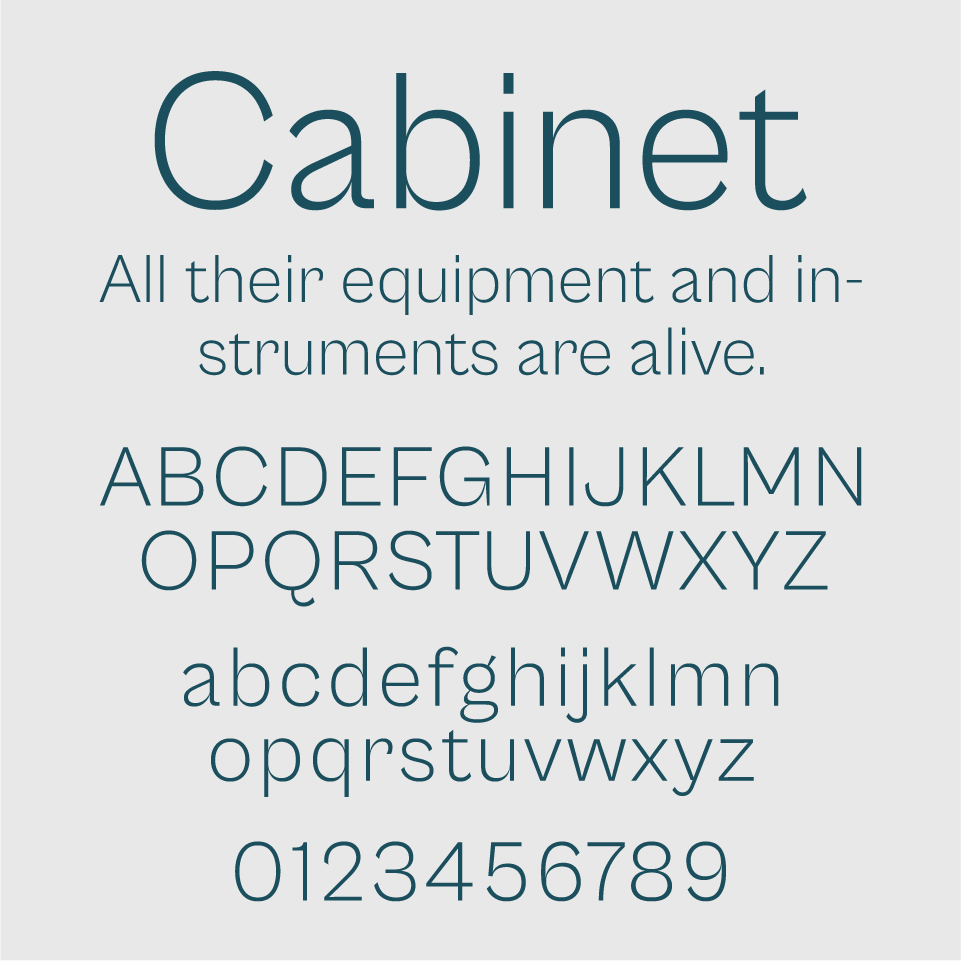
Cabinet Groteskフォントは、どこかクラシカルな雰囲気と現代的なシャープさが同居する、スマートなサンセリフ体です。文字の一部にみられるやわらかなカーブや独特の抜け感が、温かみのある印象を添えています。
情報をきちんと伝えつつ、かしこまりすぎない空気感が魅力。洗練されながらも親しみやすく、雑誌やブランドサイトなど、上品な場面でも自然に馴染むフォントです。